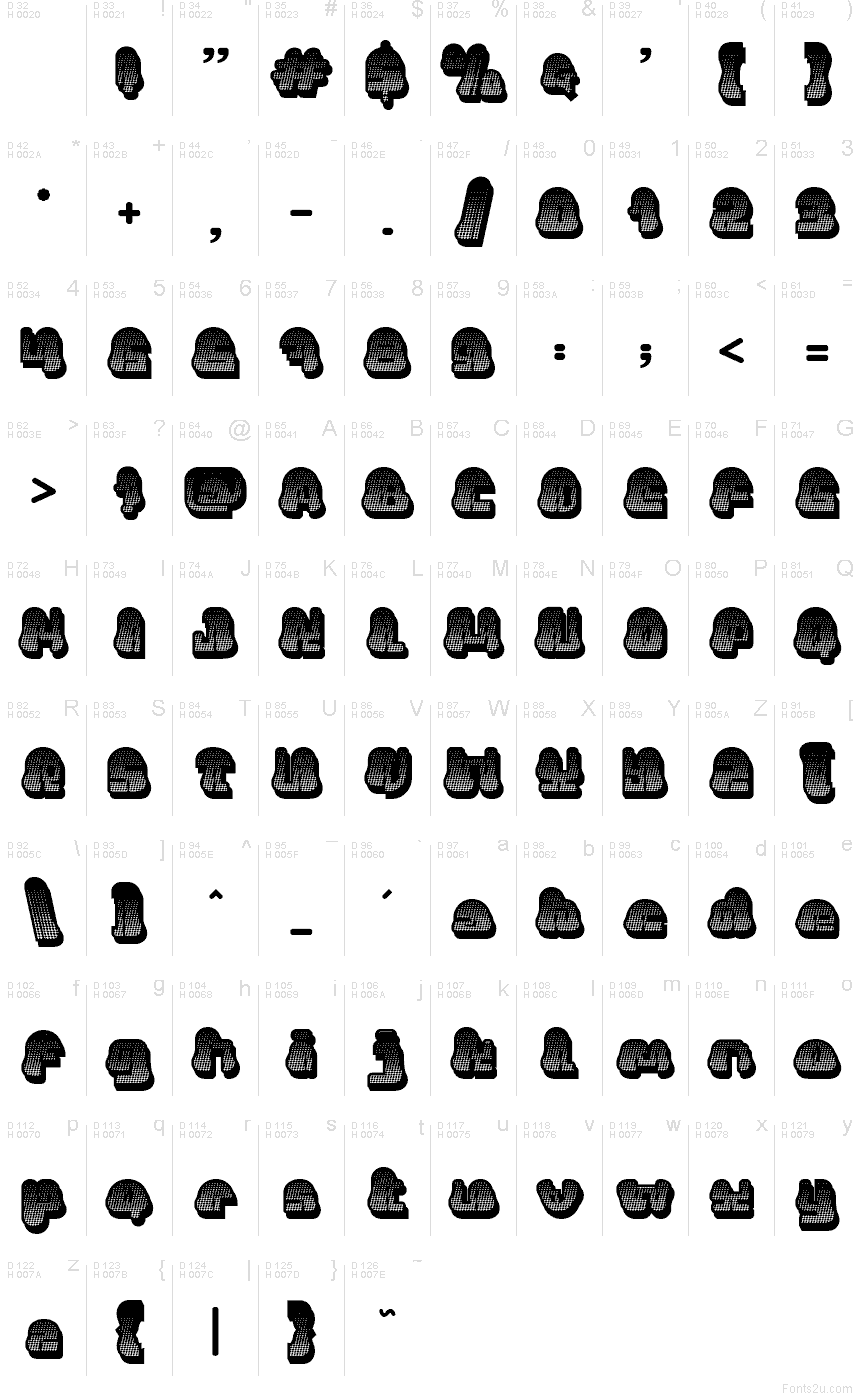
Písmo Vibe Tribe Seven od Putracetol Studio je bezplatné groovy display písmo s baňatými, zaoblenými literami, těsnými vnitřními mezerami a výraznou siluetou inspirovanou 70. lety. Polotónový rastr propůjčuje plným tvarům živou sítotiskovou texturu.
Hudební plakáty představují skvělý výchozí bod, protože široké tvary působí jako zakázková grafika pro kapelu nebo klubovou noc. Tečkovaná výplň se výborně hodí také na obaly desek, festivalový merchandise a retro branding potravin, kde se opakující se vzor může stát součástí pestrých ilustrovaných grafik.